DESIGN CUTS(でざいんかっつ)英語サイトで、新しいバンドルが発売されました。
今回のバンドルは「The Essential, Versatile Font Collection(ザ・エッセンシャル、バーサタイル・フォント・コレクション)」。
LatinotypeやTobias Saulをはじめとした多くのフォント制作会社やデザイナーと協力して実現した、あなたのデザインのクオリティを底上げするフォントがたっぷり入ったコレクションです。
「The Essential, Versatile Font Collection」の気になる中身
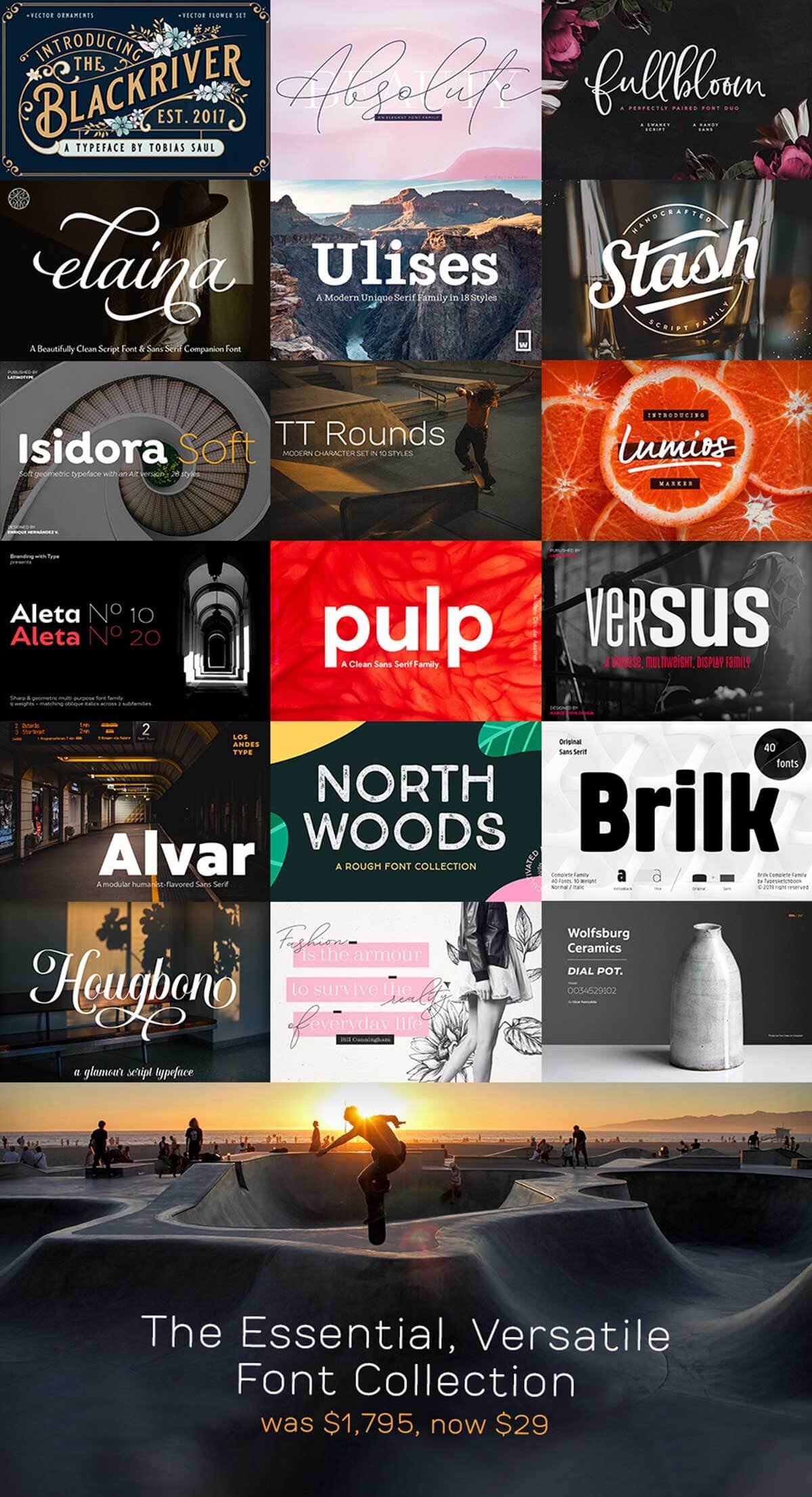
▼わたしが今回のバンドルで特に気になる素材はこちらです。ボリュームがすごすぎて、この記事では全部の素材を紹介できません。気になる素材があれば、ぜひウェブサイトをチェックしてみてくださいね。
ヴィンテージ風のデザインにぴったり:BLACKRIVER FONT + ORNAMENTS
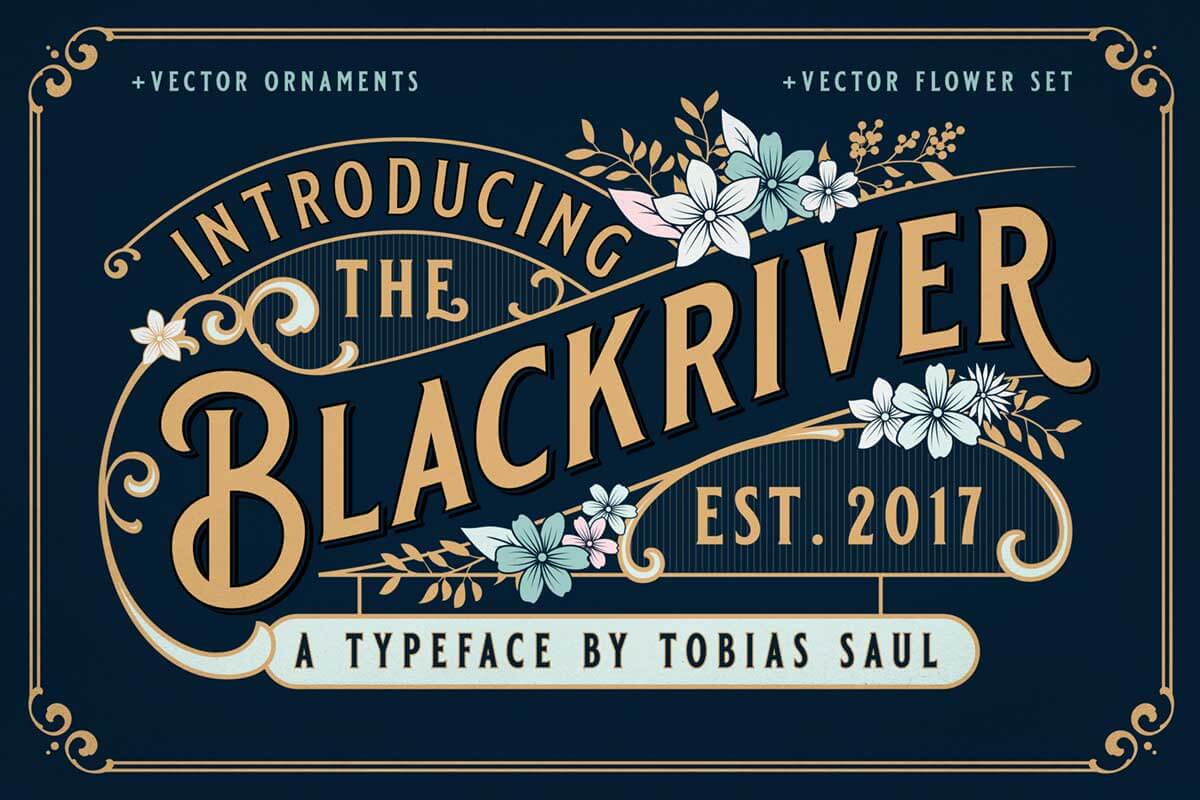
ヴィンテージ風のロゴやポスターなどを作るのにぴったりな「BLACKRIVER FONT + ORNAMENTS
」。フォントと一緒に使える花のイラストとオーナメント(各12点)もついてきますよ。
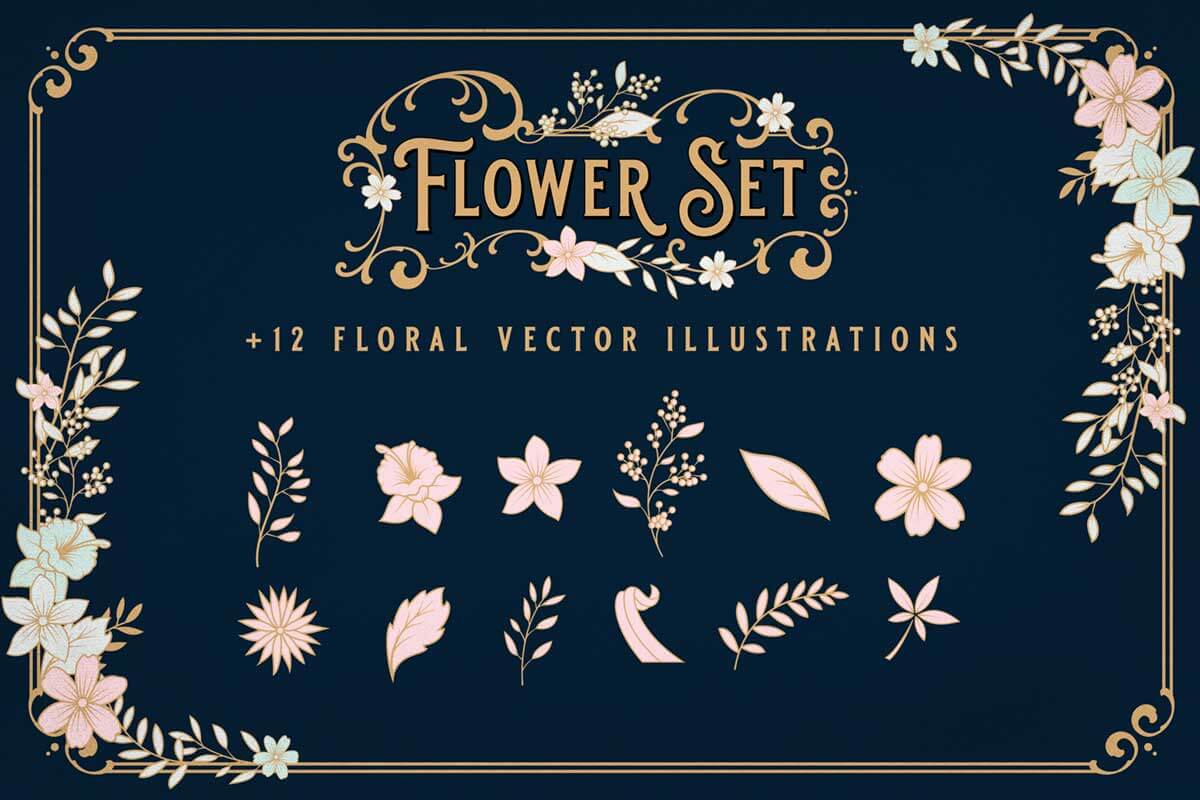
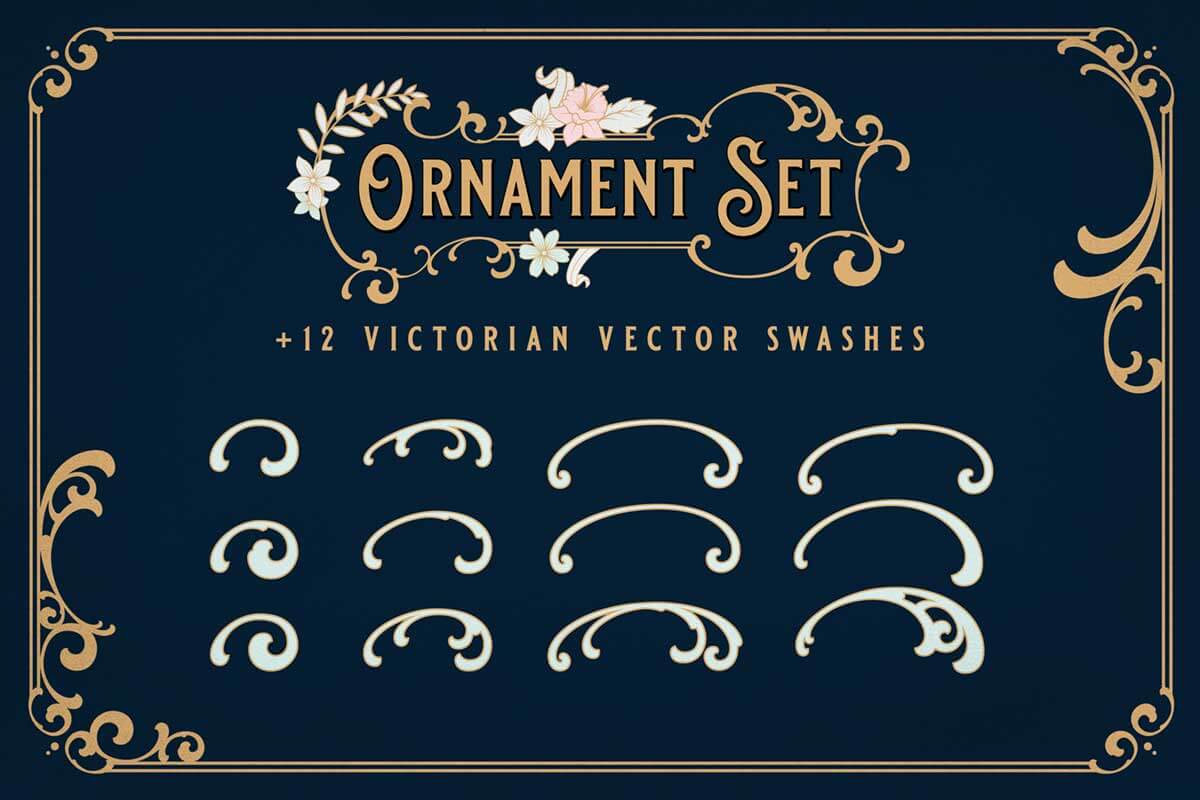
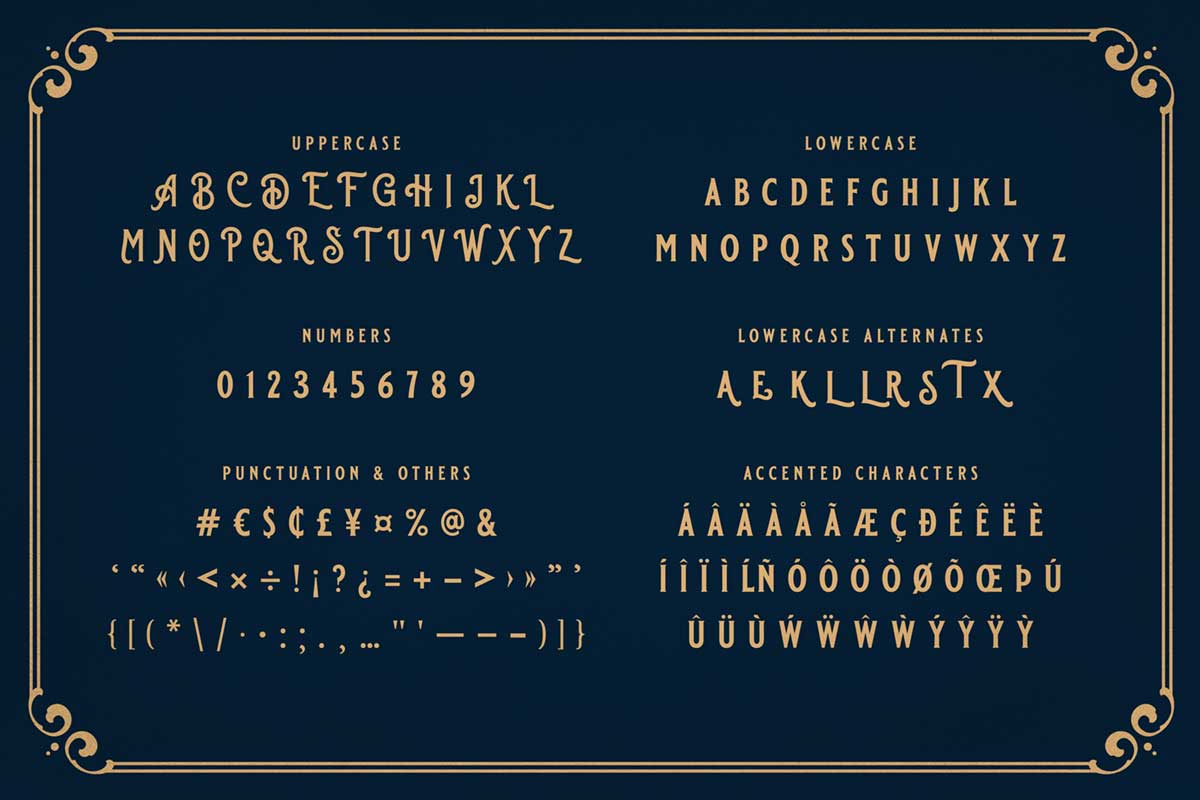
あえて違うウェイトを組み合わせて楽しみたい:VERSUS
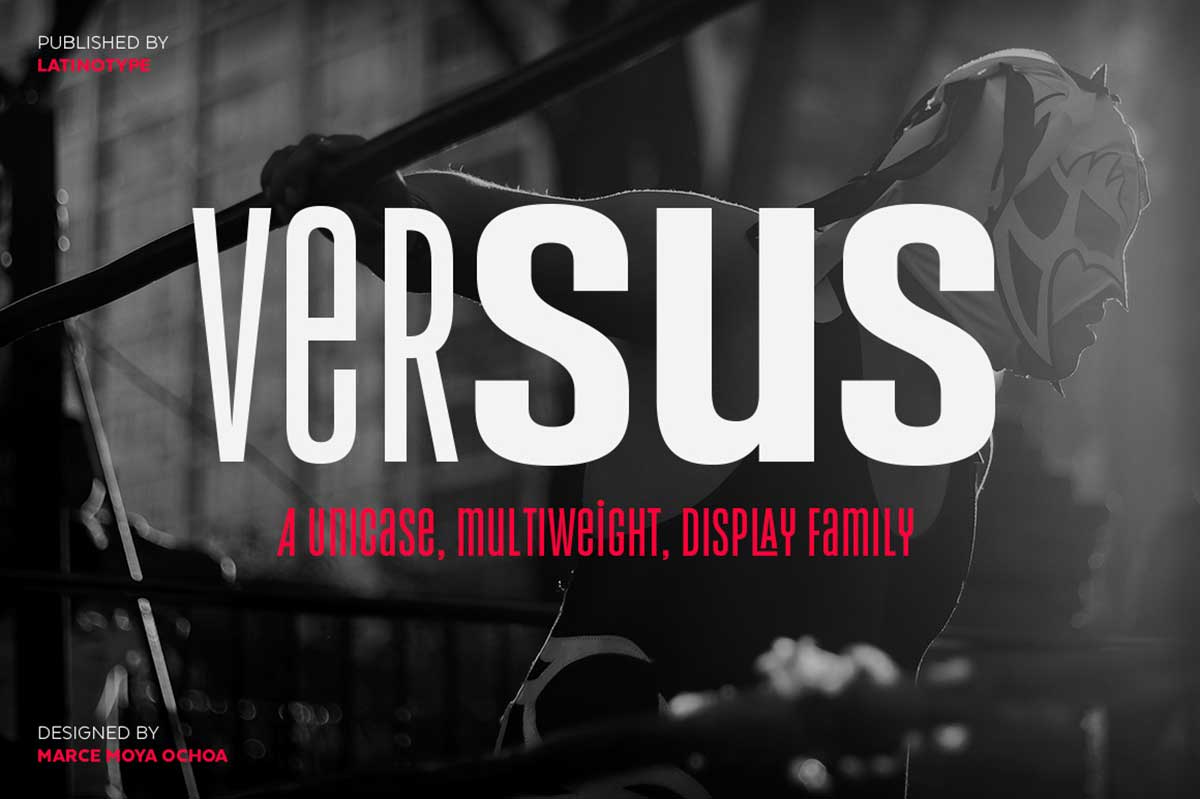
9種類のウェイトが揃い、200以上の言語に対応した「VERSUS」。豊富な字形オプションやリガチャ(合字)も用意されています。あえてウェイト違いの文字同士をくみ合わせて、普段とは違う表現にチャレンジしたくなるフォントです。
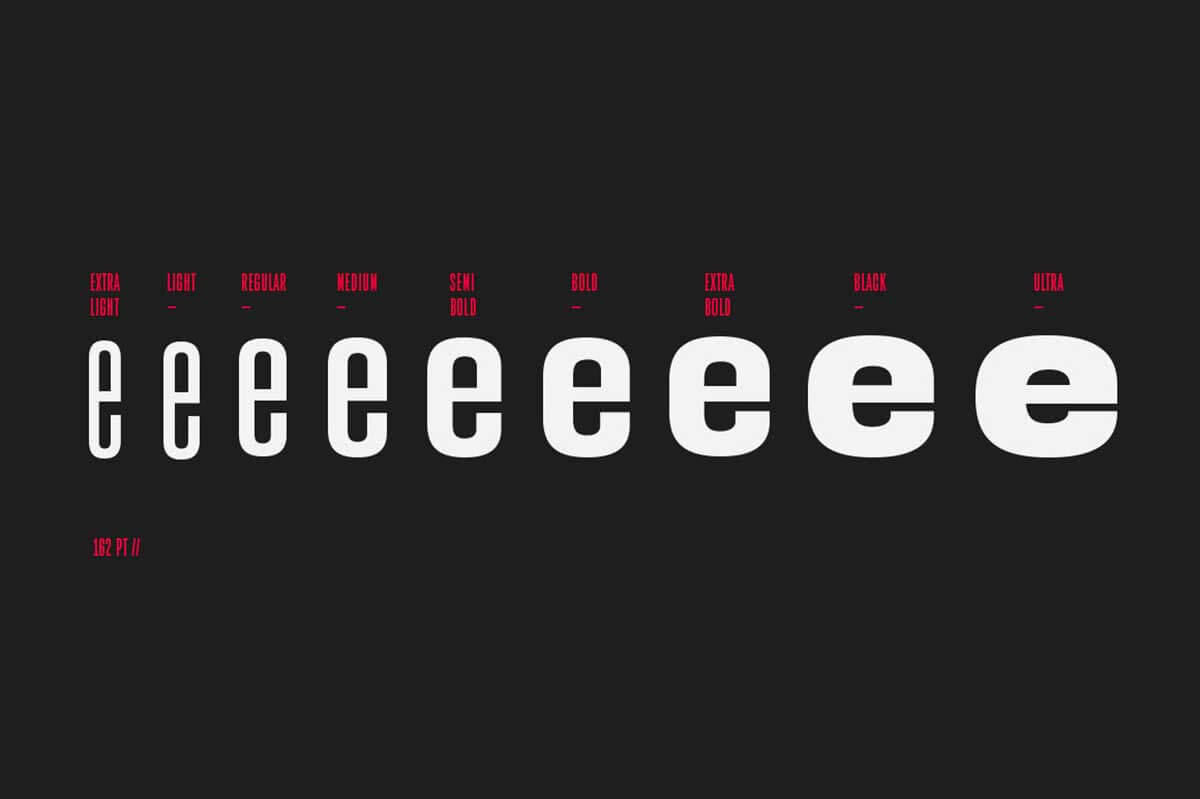
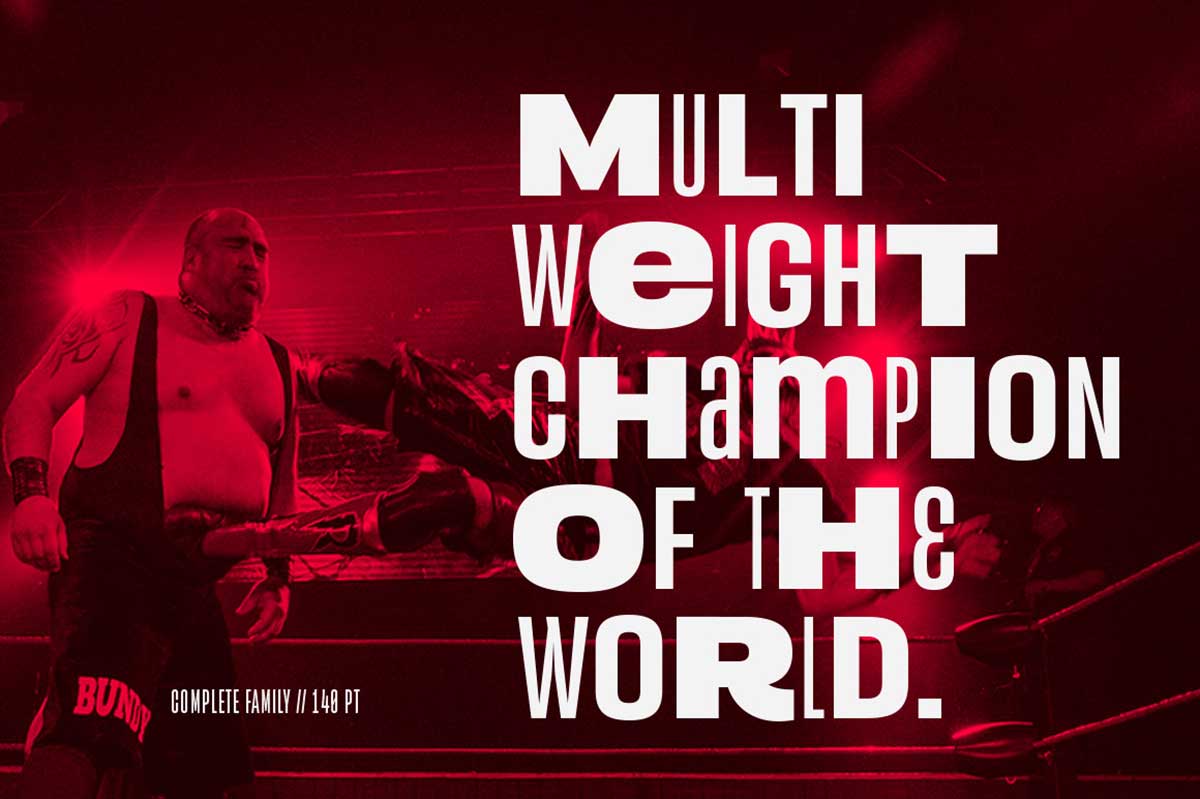
ISIDORA SOFT
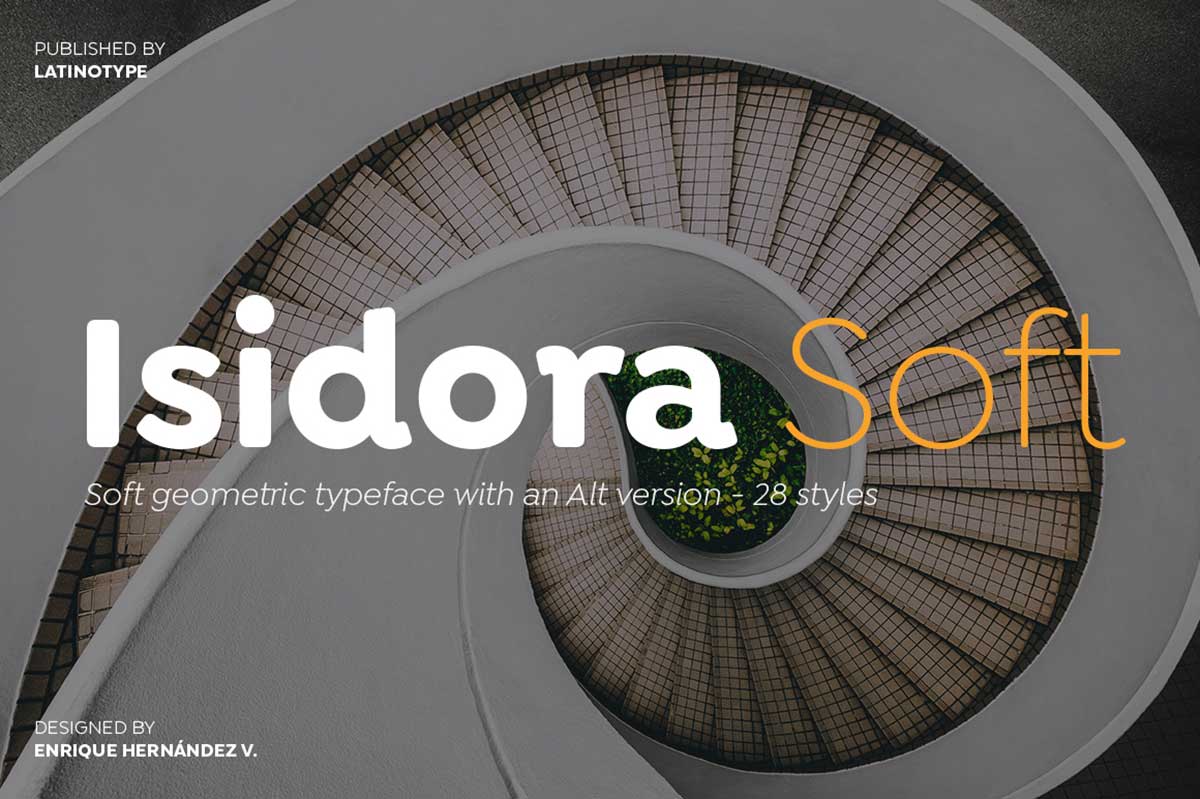
角に丸みを帯びたやさしい印象の「ISIDORA SOFT」。全てのフォントにalternativeがあり、用途に応じて使いわけできます。
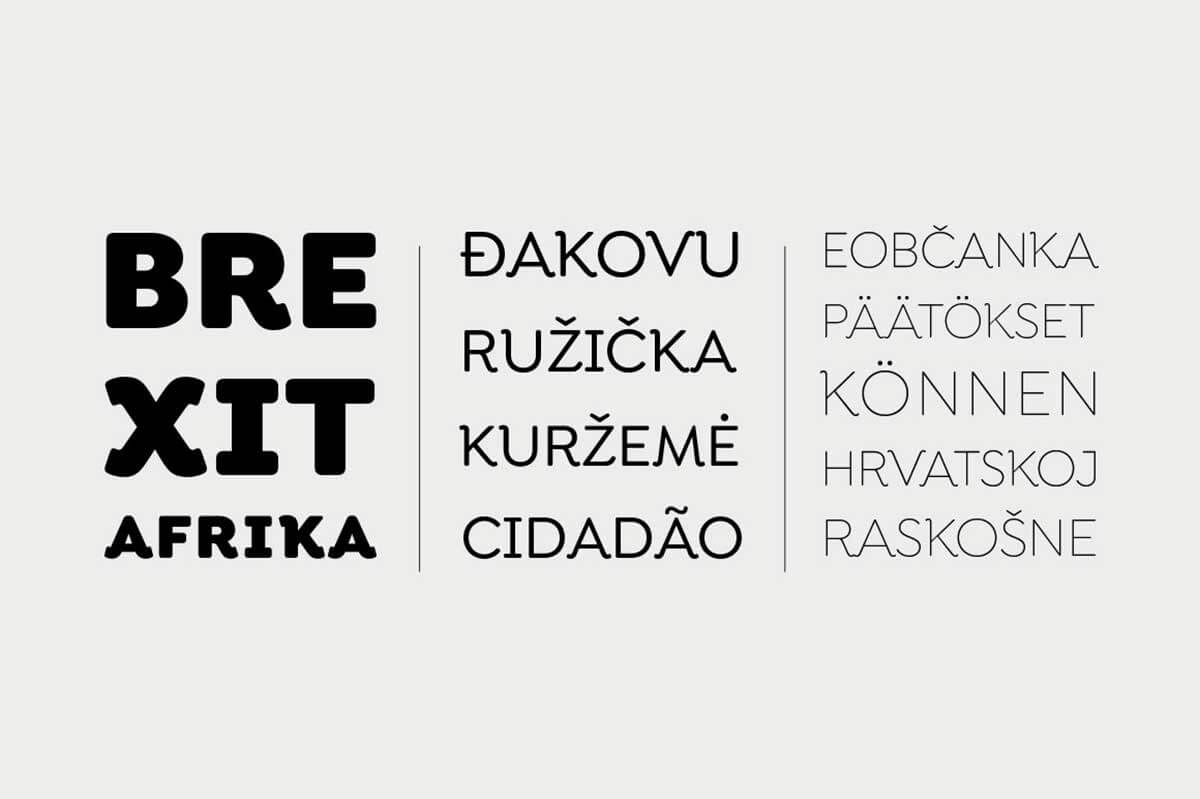
優雅なタイポグラフィが簡単にできる:HOUGBON – A GLAMOUR SCRIPT
一見難しそうな、文字の前後左右に飾りを多用したロゴや見出しが簡単にデザインできるフォント「HOUGBON – A GLAMOUR SCRIPT」。媒体や周囲のデザイン要素とのバランスを見ながら、1字ずつ自由に飾りを選べます。